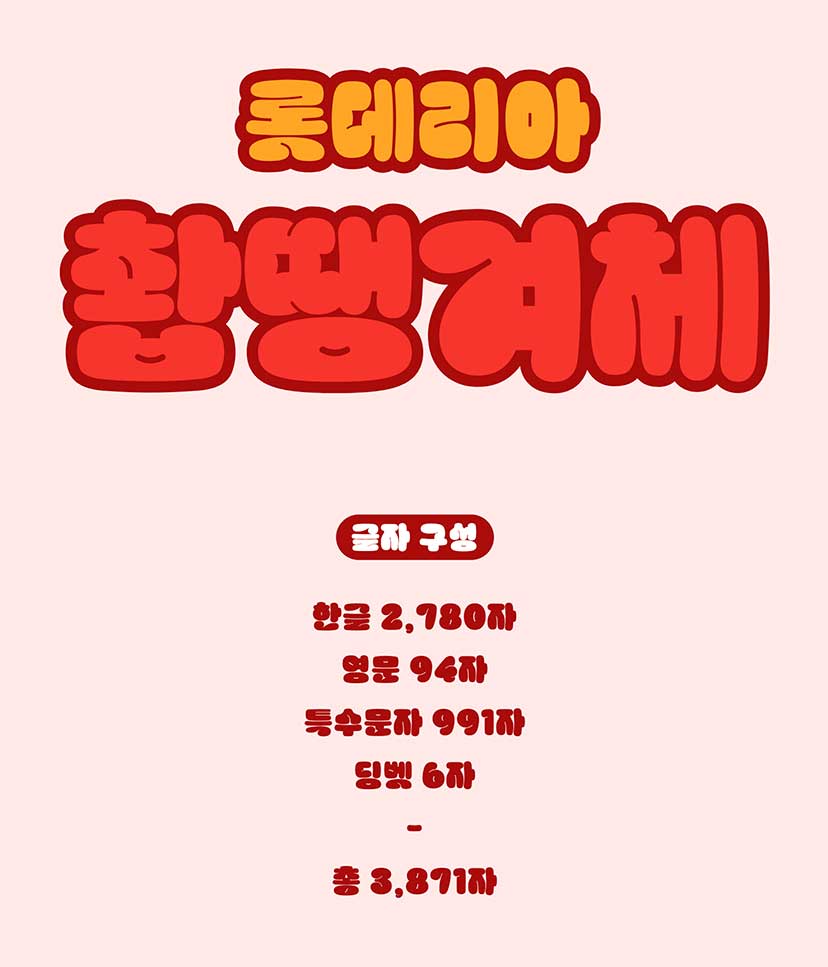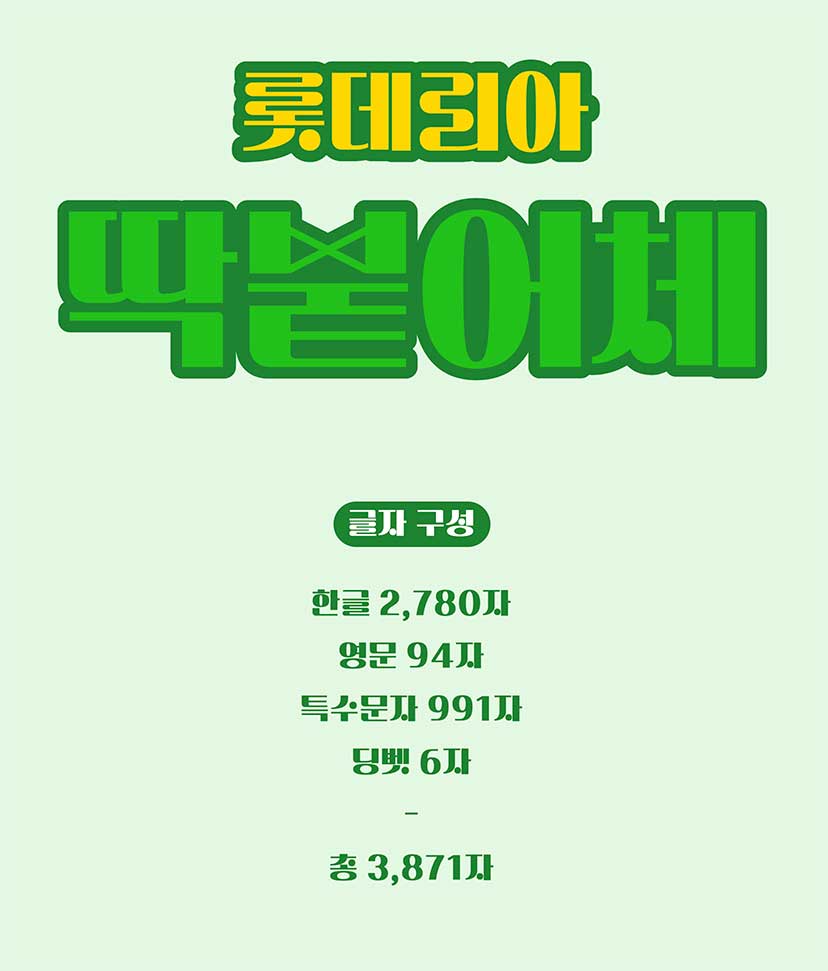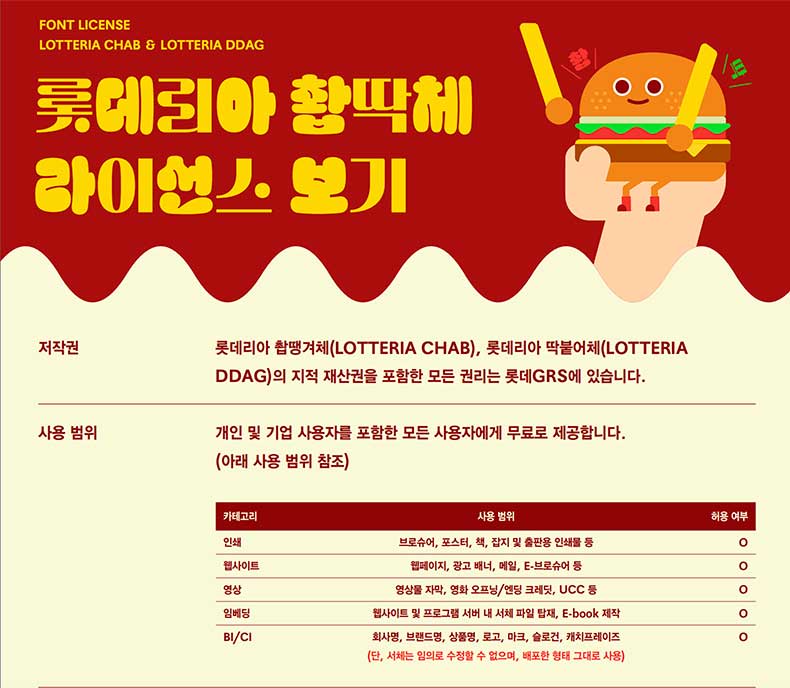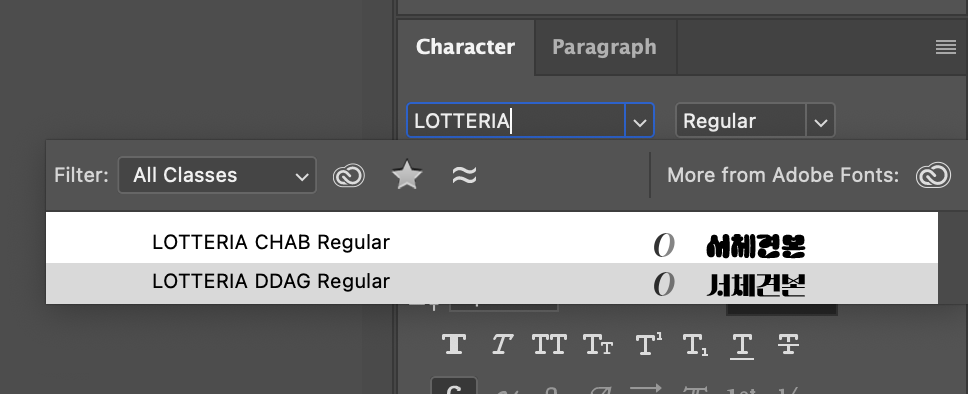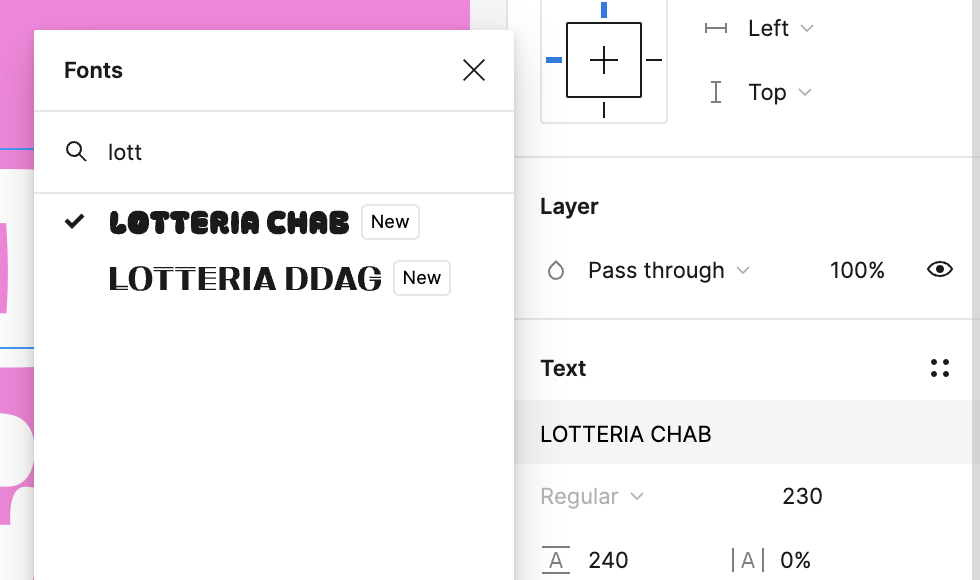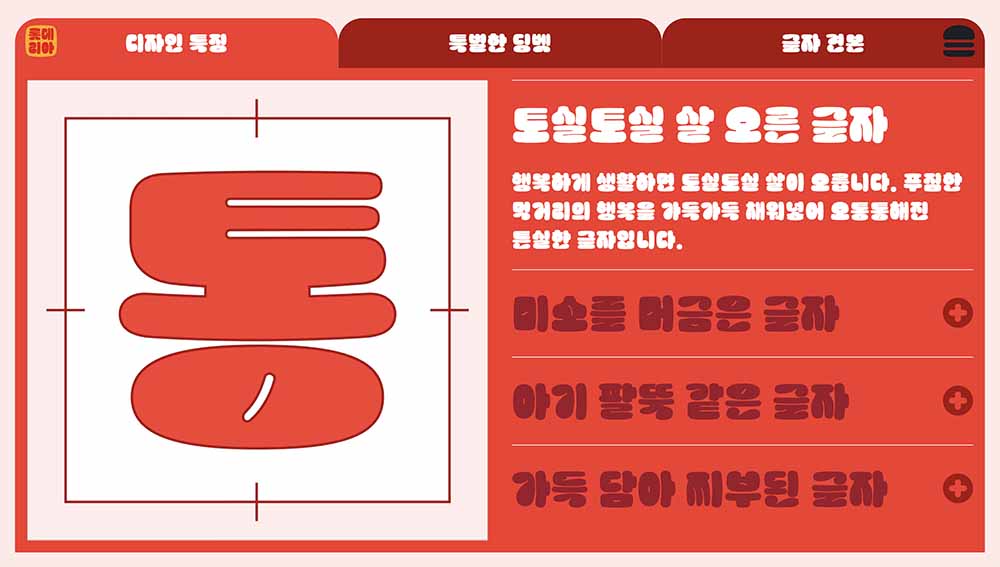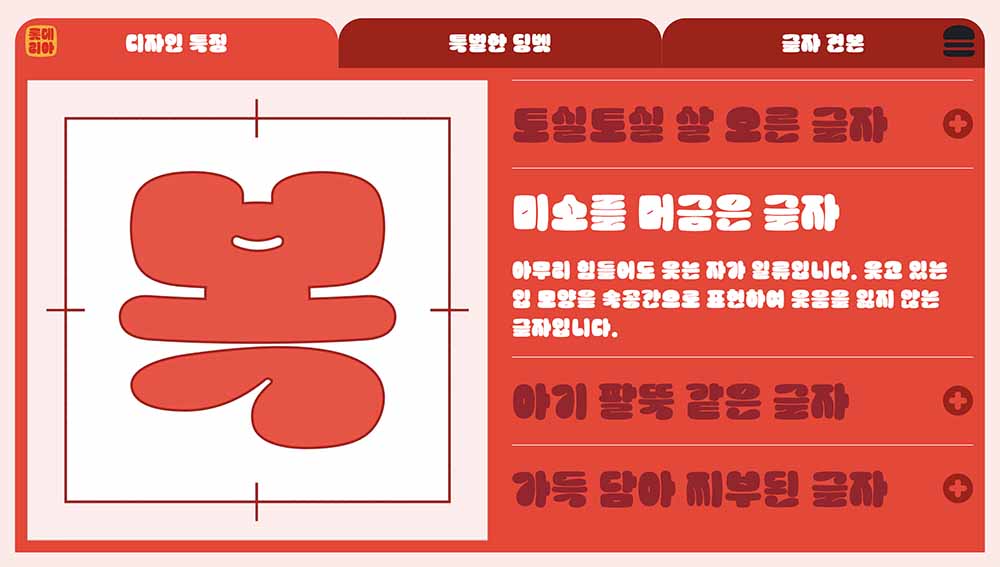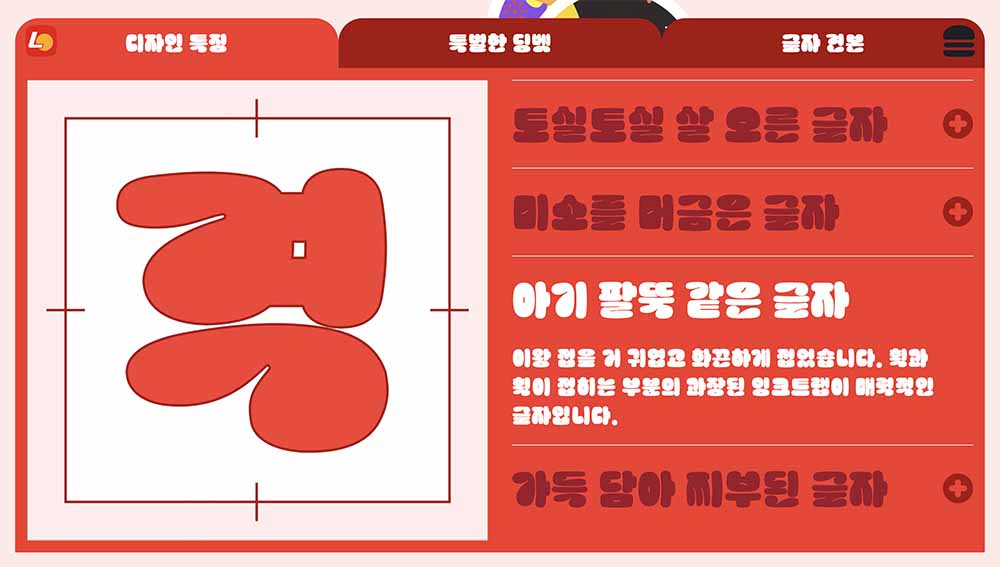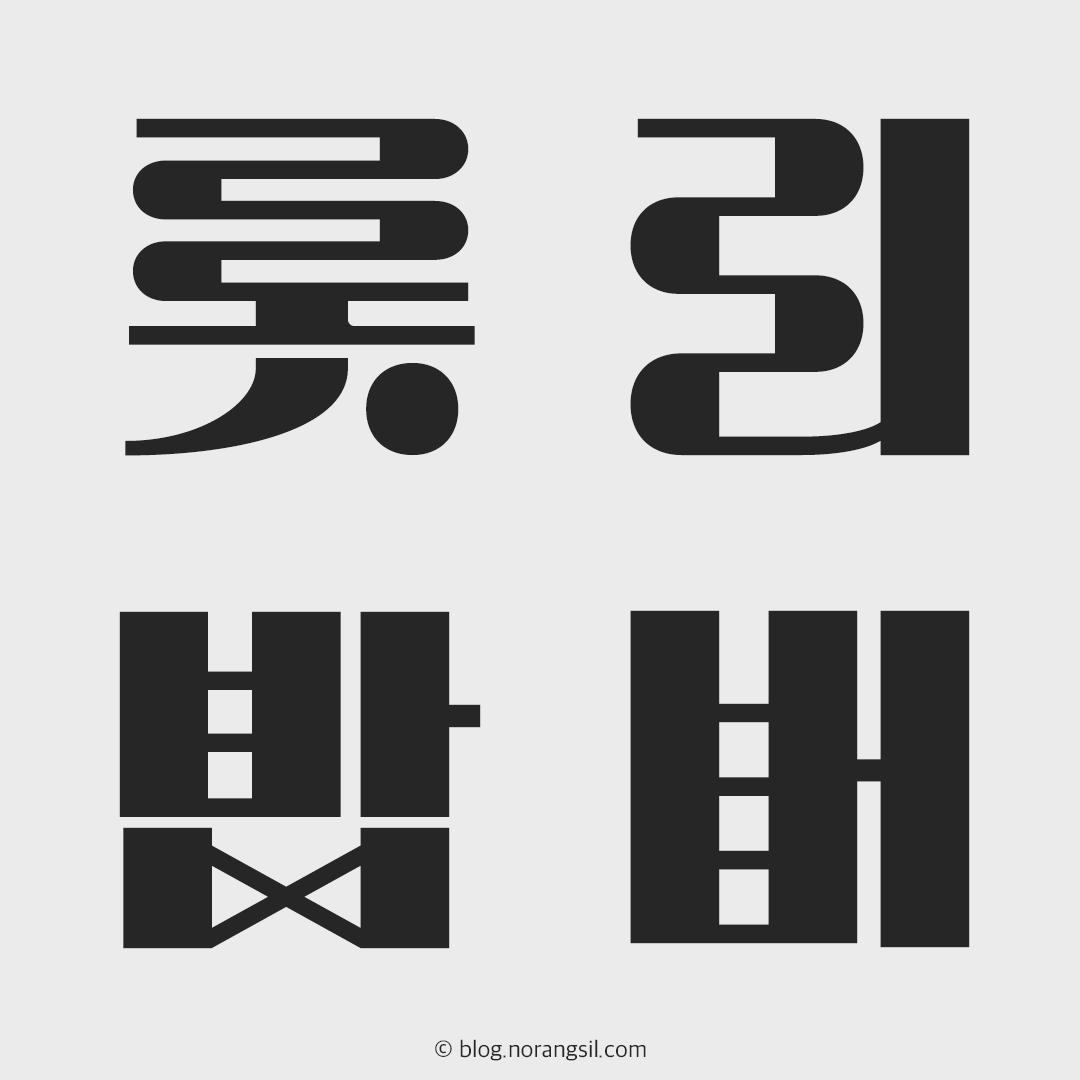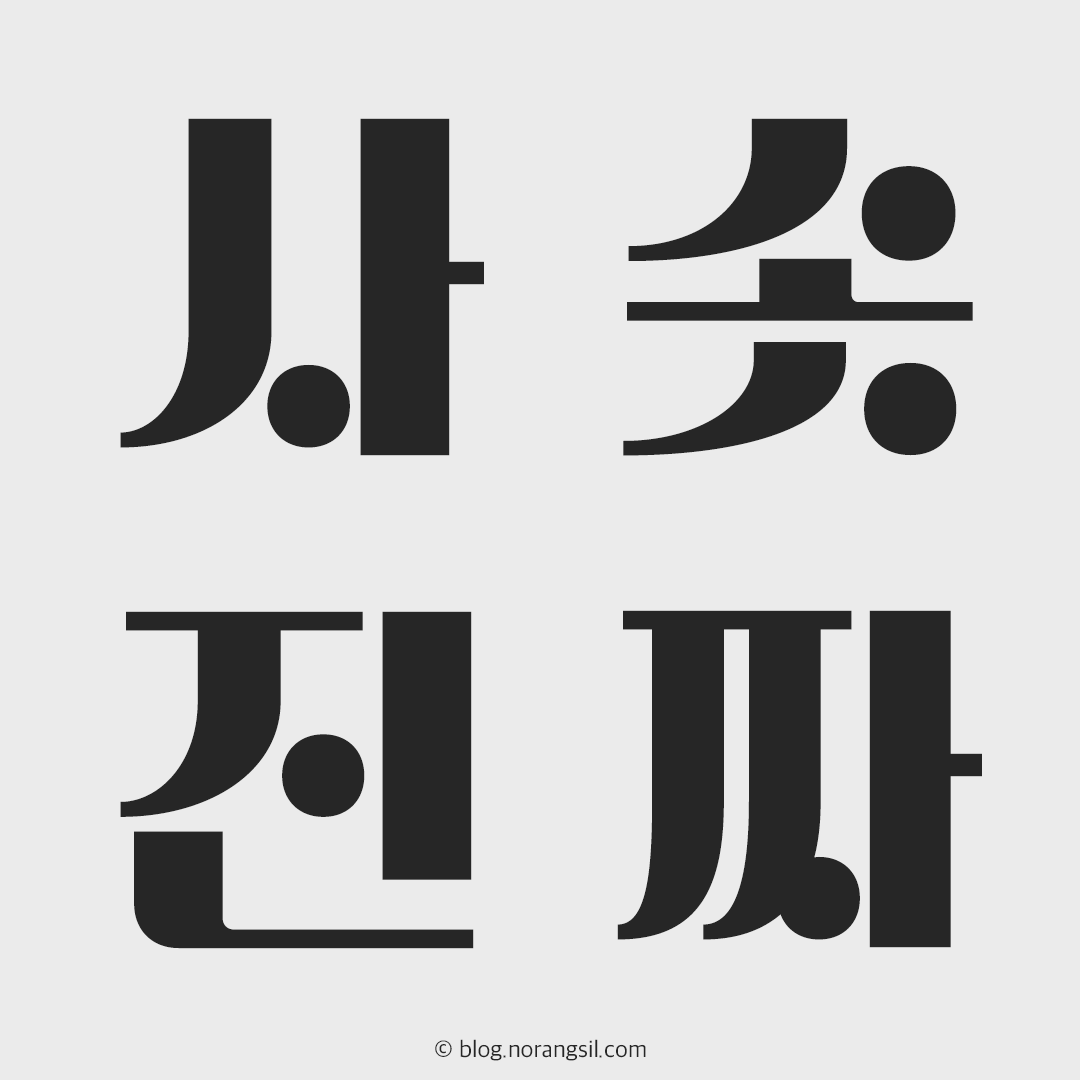
무료 한글폰트 롯데리아 촵딱체 - 촵땡겨체 딱붙어체 다운로드
롯데리아 폰트 2가지를 소개합니다.
① 롯데리아 촵땡겨체 (LOTTERIA CHAB)
② 롯데리아 딱붙어체 (LOTTERIA DDAG)
이 둘을 합쳐서 촵딱체라고 이름 붙인 것 같아요.
촵딱체를 만든 배경에 관해 롯데리아 폰트 홈페이지에 이렇게 소개합니다.
평범한 글자에는 담을 수 없던 롯데리아 스피릿! 개척정신과 도전정신을 담은 한글폰트!
평범한 폰트는 롯데리아 브랜드 이미지를 표현할 수 없다는 생각! 이점만 봐도 도전정신은 확실해 보입니다. 그래서 폰트이름도 개성이 넘치는 건가요? 🤔
촵땡겨체❣️ 딱붙어체❣️
촵! 딱! 폰트명이 독특해서 이게 영어로 어떻게 표시되나 궁금했는데요.
✅ LOTTERIA CHAB
이건 촵땡겨체
✅ LOTTERIA DDAG
이건 딱붙어체 입니다.
촵딱체 폰트 개발회사는 윤디자인입니다. 이제 폰트를 하나씩 살펴볼게요. 먼저 촵땡겨체 입니다.
롯데리아 촵땡겨체
촵땡겨체(LOTTERIA CHAB)는 솜사탕처럼 부풀어오른 획들이 서로를 쓰다듬어 주는 느낌입니다. 마치 햄버거 빵처럼 폭신폭신함이 느껴져요. 뭔가 뭉뚝한 느낌도 있네요. 아마도 공간을 꽉 채우는 도톰한 두께이다 보니 복잡한 글자에서 그런 느낌이 느껴지는 것 같습니다. 뭉뚝함이 친근한 느낌을 줍니다.
여기까지는 제가 느낀 부분이고, 이제 롯데리아의 폰트 소개를 볼게요.
촵땡겨체 디자인 세계관이 느껴지는 재미있는 이야기가 담겨있네요. 웃고 있는 입 모양을 글자의 속공간에 표현했데요. ㅂ의 가운데를 살펴보세요.
진정한 고수는 망가지는 것을 두려워하지 않는데요! 가로획이 쌓일수록 찌부되며 터질 것 같은 치명적인 매력의 한글 폰트랍니다. 폰트 소개하는 글이 참 재미있네요😄
촵땡겨체 딩뱃 문자
촵땡겨체는 6가지 딩뱃 문자를 제공합니다.
*촵
*복
*굿
*기운촵
*롯데리아
*포테이토
아주 귀여운 그림문자가 짜잔 나타날 겁니다.
롯데리아 딱붙어체
딱붙어체(LOTTERIA DDAG)는 햄버거를 닮은 글자라고 소개하고 있는데요. ㄹ과 ㅂ의 모양을 보면 빵과 패티, 치즈, 채소 등 내용물이 층층이 쌓여있는 모습이 연상됩니다. 정말 딱이에요.
개인적으로 딱붙어체의 ㅅ과 ㅈ도 마음에 듭니다. 잘 매만저 묶어둔 커튼의 실루엣처럼 느껴지는 비스듬한 곡선과 그 아래에 있는 커다란 점. 취향저격입니다.
롯데리아 딱붙어체 소개를 볼게요.
관심을 바라는 글자! 라고 대놓고 말하는 자신감 넘치는 롯데리아 딱붙어체 입니다.
딱붙어체 딩뱃문자
딱붙어체도 6개의 딩뱃문자를 제공합니다. 별(*) 포함 아래 단어를 입력해 보세요. 귀여운 그림문자가 짠 나타납니다.
*딱
*화이팅
*엄지척
*행복딱
*롯데리아
*포테이토
딱붙어체 딩뱃문자 몇 개만 살짝 볼까요?
촵딱체로 만든 생일축하카드
얼마 전 지인의 생일에 전해주려고 축하카드를 만들었어요. 즐거운 느낌을 전달하기 딱 좋을 것 같아 촵땡겨체를 썼는데, 결과물이 만족스러웠어요.
다 만든 후 딱붙어체로 폰트를 바꿔 봤어요. 두 폰트의 개성이 다르다 보니 색상도 바꾸게 되었죠. 그랬더니 문구가 눈에 확 들어오는 것이 딱붙어체도 좋았습니다.